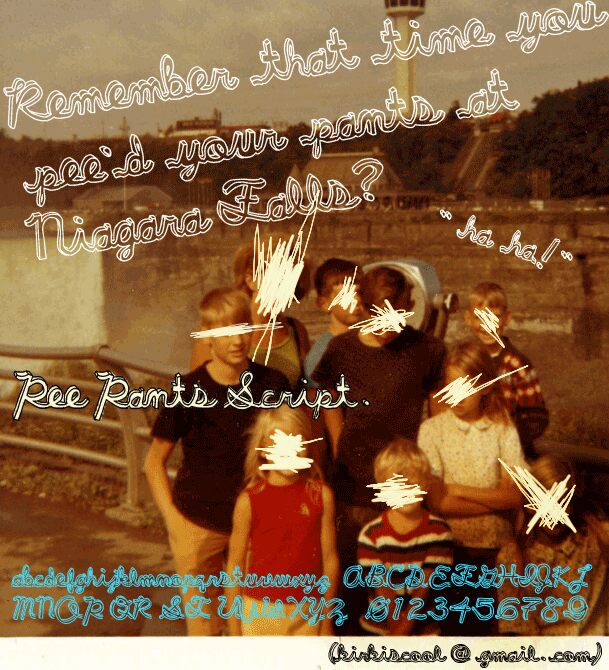
Pee Pants Script to darmowy konturowy krój pisma typu script display z połączonymi, zapętlonymi literami i dynamicznym, odręcznym zamachem. Podwójna dolna krawędź tworzy prosty, przestrzenny cień, a pociągnięcia przypominają wycinane szyldy lub napisy z naklejek.
Pasuje do zabawnych marek odzieżowych i gadżetów opartych na humorze lub młodzieżowej grafice. Efekt jest natychmiastowy i wyrazisty. Może również kształtować plakaty wydarzeń i gadżety rozrywkowe, szczególnie dla odbiorców pociągniętych ilustracją komiksową i swobodnym stylem streetwearowym.